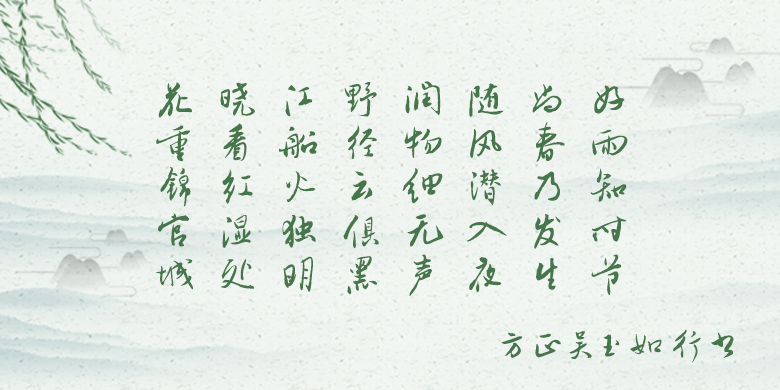
方正吴玉如行书,主要源自其手札。在保持原风格的基础上,仿制缺字,同时按字库要求修改了部分异体、繁体字,形成合计近万字的涵盖常用繁简字的字库。
吴玉如(1898年—1982年8月8日),字家琭,后以字行。生于南京,原籍安徽泾县茂林村,故早年号茂林居士,晚年自署迂叟。中国现当代学者、书法家。吴玉如一生研习书法,熔合诸家风格,而以二王为依归,形成了端丽秀劲、空灵飘逸的独特书风。吴玉如半生教书,提携后学,桃李遍天下,当代著名书法家欧阳中石即其学生之一,中石书风,亦是化用自其师。
方正吴玉如行书
设计师: 郭毓海
分类:常规书写·毛笔